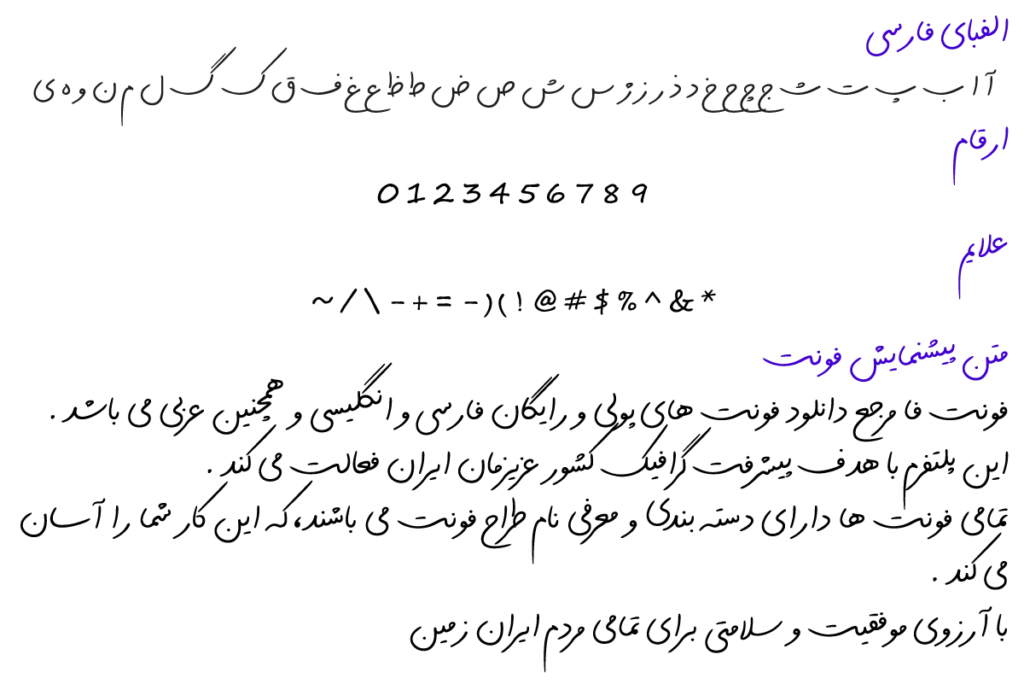
پیشنمایش فونت مانلی
فونت فارسی مانلی - Maneli
توضیحات و معرفی فونت مانلی
فونت فارسی مانلی ( Maneli ) از مجموعه فونت های می باشد، همچنین نوع فونت دست نویس و متن می باشد.
فونت فوق العاده زیبای معرفی شده توسط محمد عموئی در سال 1401 طراحی و ساخته شده است.
توضیحات سازنده این تایپ فیس
این فونت با شباهت زیاد به دست خط طبیعی، تجربه ای روان و دلنشین از نوشتار دست نویس را ارائه می دهد.
برخلاف بسیاری از فونت های این سبک که حروف روی یک خط کرسی ثابت طراحی و متصل می‌شوند، مانلی از کرسی سیال بهره می‌برد؛ ویژگی ای که ساختارهای سنتی مانند خط نستعلیق را نیز شکل می‌دهد.
این فونت علاوه بر کرسی سیال، دارای ترکیبات متعدد، قابلیت کشیدگی و حروف جایگزین متنوع است که انعطاف و غنای بصری آن را افزایش می‌دهد.
در تصویر زیر از این تایپ فیس برای نگارش شعر زیبای نام جاوید وطن استفاده شده است.
پیشنمایش فونت مانلی
حروف جایگزین در فونت مانلی
در نسخه جدید فونت، مجموعه ای از حروف و ترکیبات جایگزین متنوع اضافه شده است.
همراه با فونت، یک فایل راهنما ارائه می‌شود که در آن نحوه استفاده از حروف جایگزین توضیح داده شده است و شما می‌توانید به راحتی تشخیص دهید کدام حروف قابل تغییر هستند.
در این راهنما می توانید نحوه تایپ حرف جایگزین “ی” را مشاهده کنید. (مثل تصویر زیر…)
حروف جایگزین در فونت مانلی
آموزش کشیدگی در فونت Maneli
آموزش کشیدگی در فونت مانلی